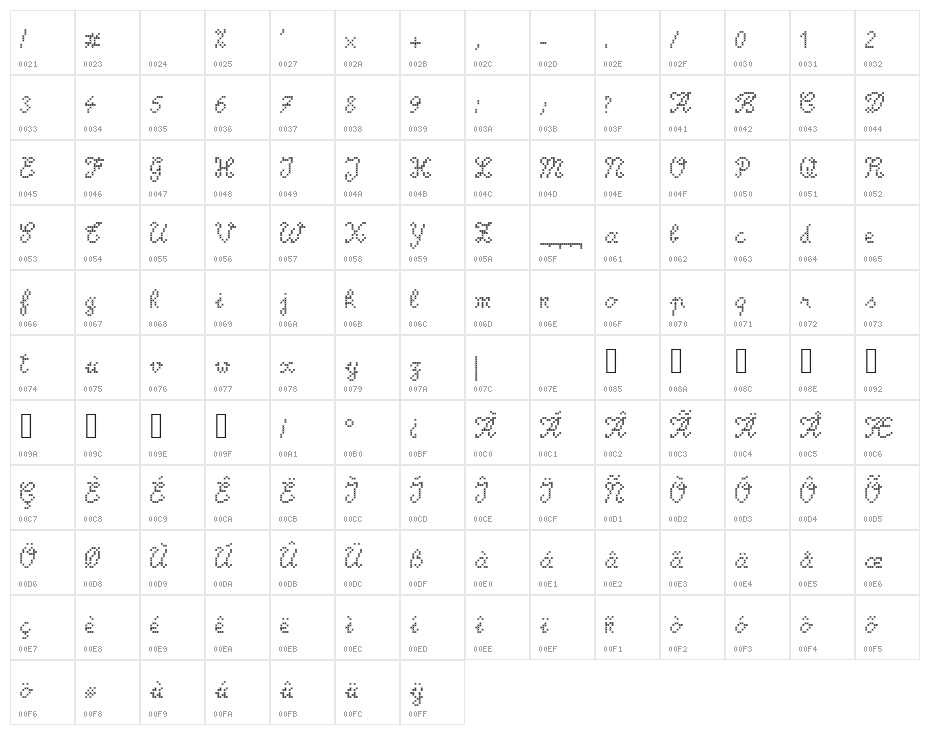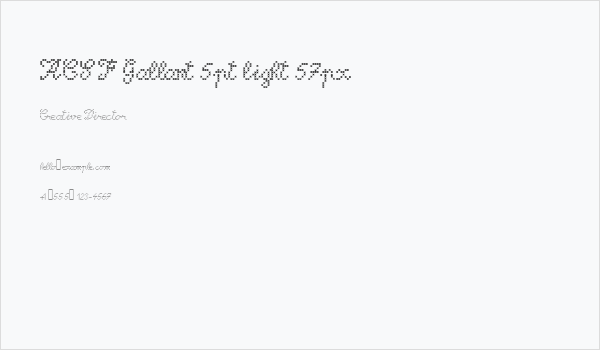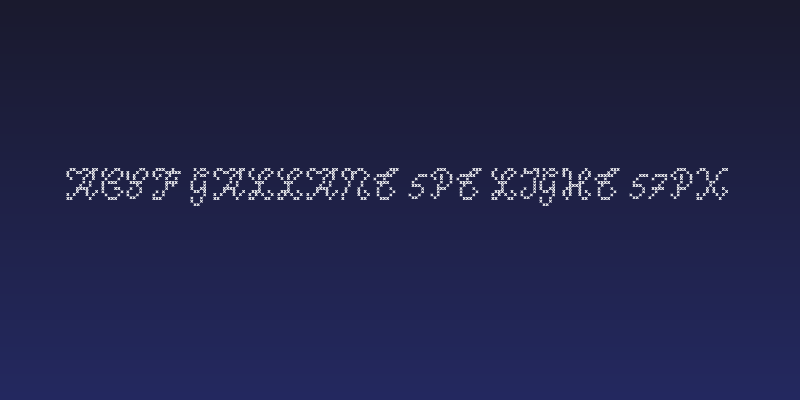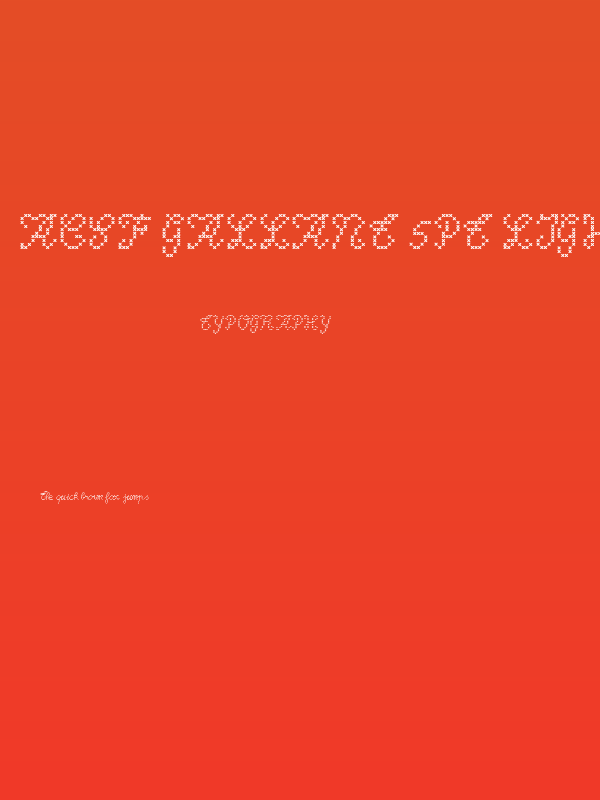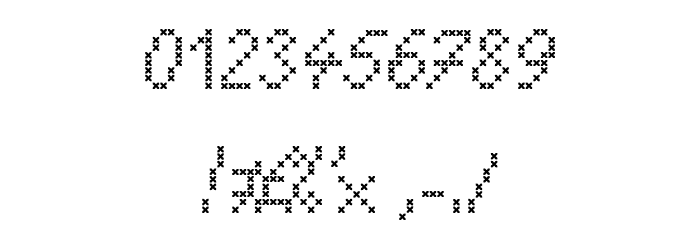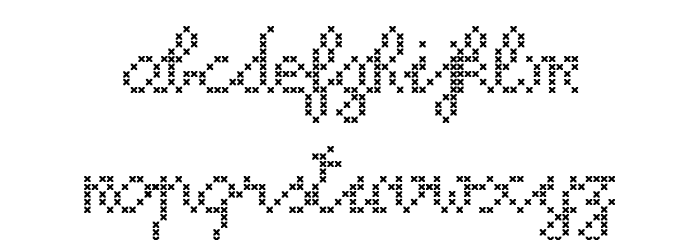
ACSF Gallant 5pt light 57px Font
| Style général | Retro, Digital |
| Cas d'utilisation | Logos, Headlines, Digital Art |
| Projets proposés | Ideal for retro-themed designs, video game graphics, digital art projects, and any creative work that seeks to capture a vintage digital aesthetic. |